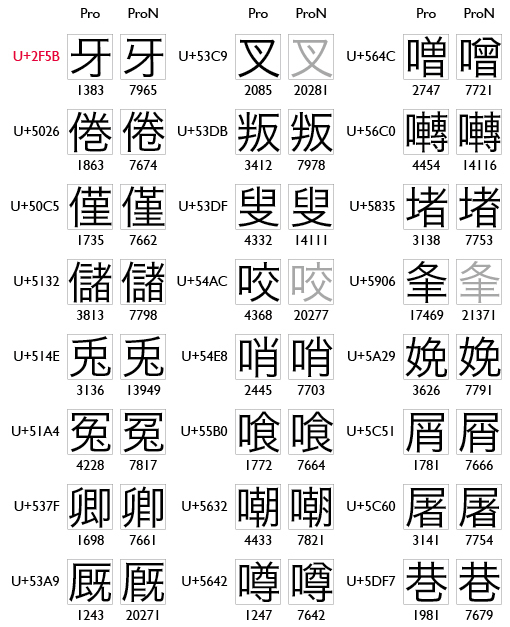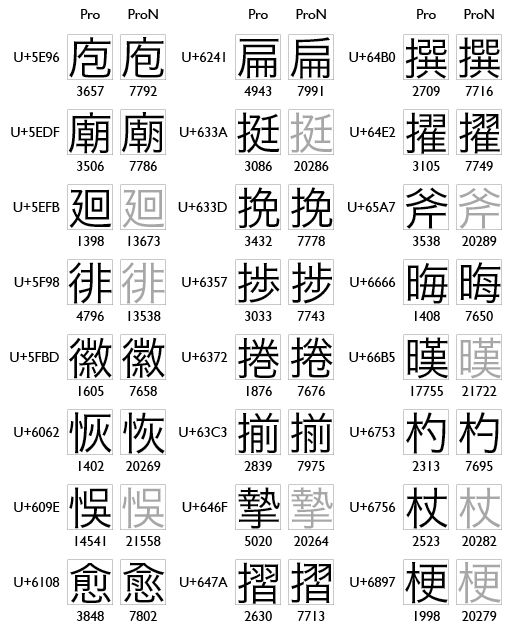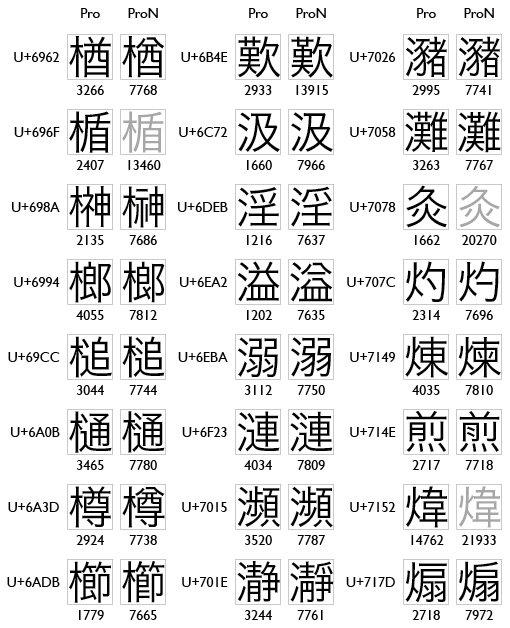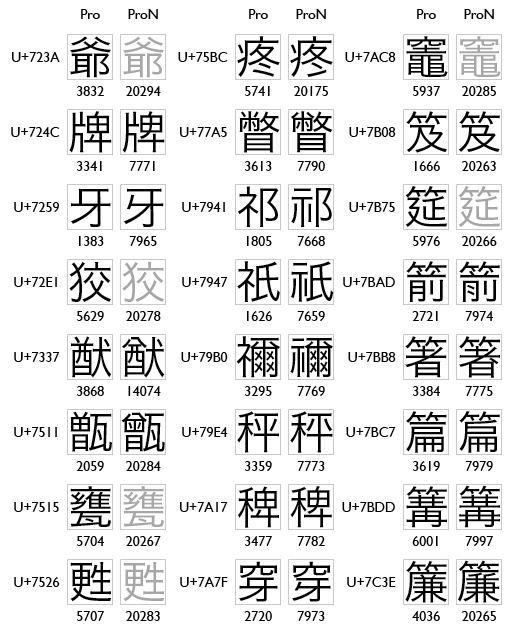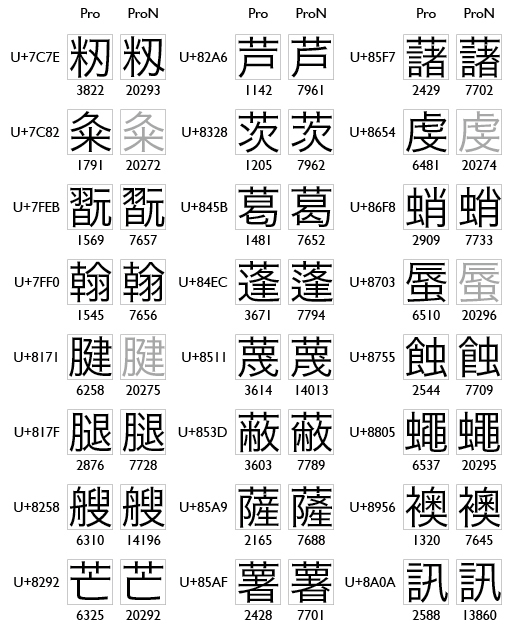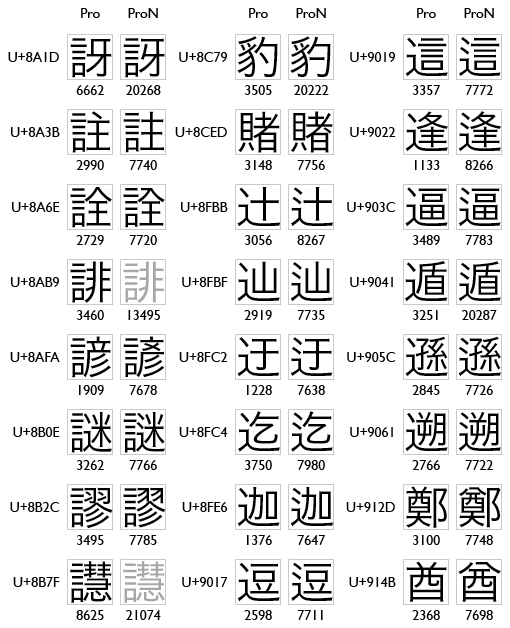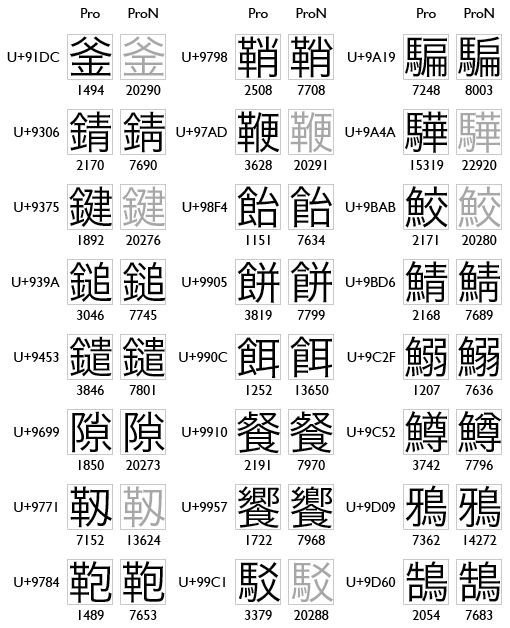
ヒラギノProとProNの違い
- ヒラギノProのデフォルトのグリフは、JIS X 0208:1990/1997およびJIS X 0213:2000の例示字形を参照している。ヒラギノProNのデフォルトのグリフは、JIS X 0213:2004の例示字形を経由して表外漢字字体表の例示字形を参照している。
- どの字の形がどう違うのかは、さまざまな資料から知ることができるが、ヒラギノそのものによるリストは見たことがなかったので作ってみた。使用したフォントは「ヒラギノ角ゴ Pro W3」と「ヒラギノ角ゴ ProN W3」。
- ProN欄の文字がグレーになっている例は、(CIDでは区別されるけれど)ヒラギノの実装字形では区別されないもの。